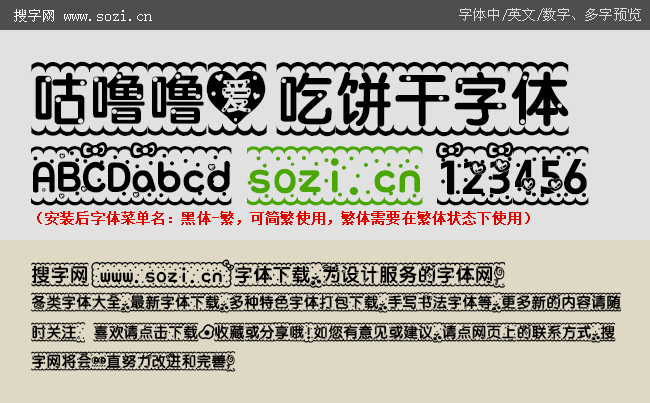
咕嚕嚕愛吃餅干字體
搜字網(wǎng)給大家提供一款很有趣的手機(jī)中文字體下載。咕嚕嚕愛吃餅干字體,這款手機(jī)字體是在粗圓體字體筆畫間插入了卡通花紋和可愛的花邊。趣味性實足,該手機(jī)字體個性實足,趣味性強(qiáng),又保持了文字的識別度,特別適合喜歡手機(jī)字體個性一些的朋友在手機(jī)上安裝使用。